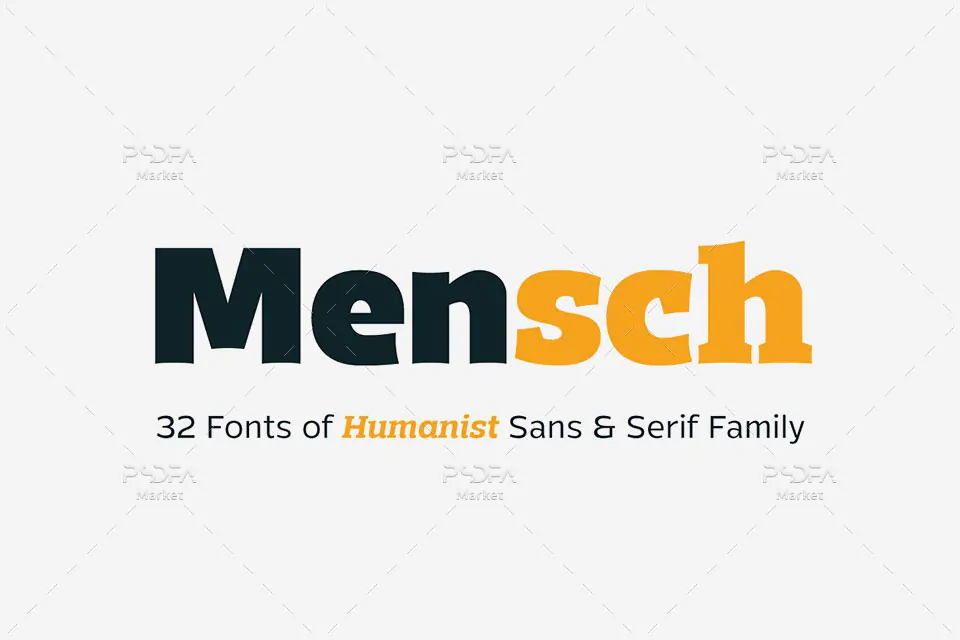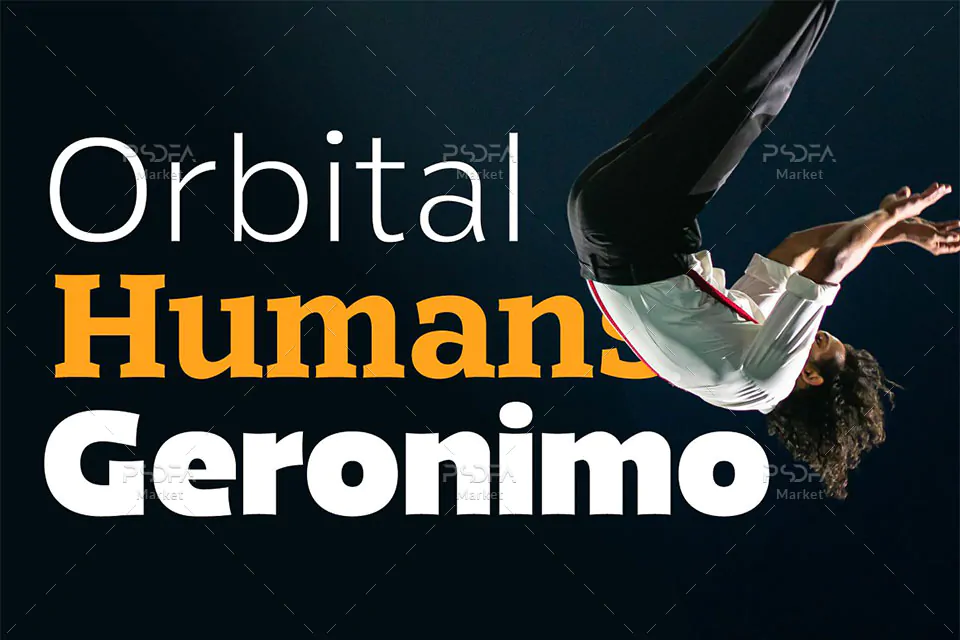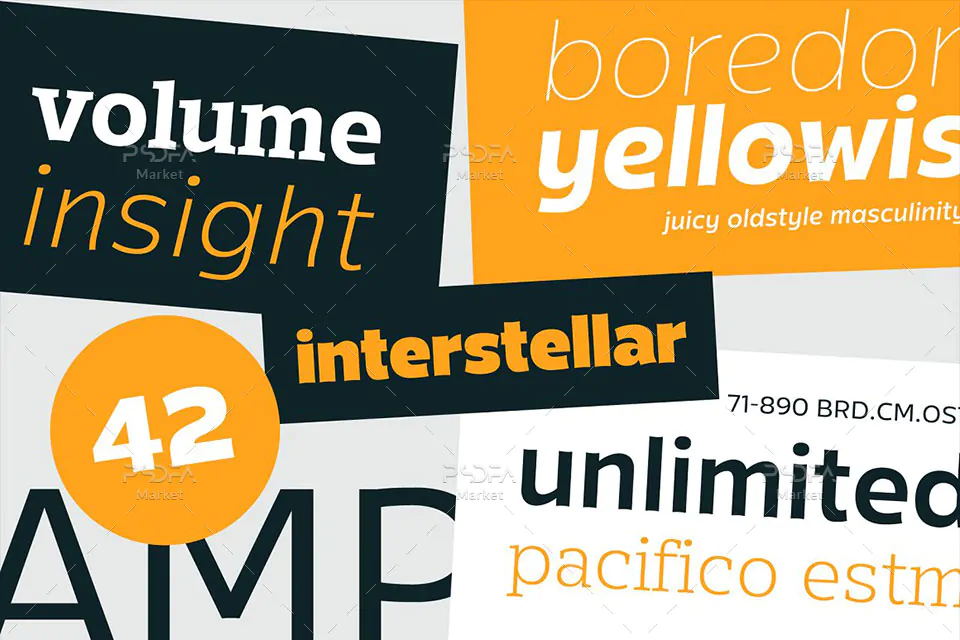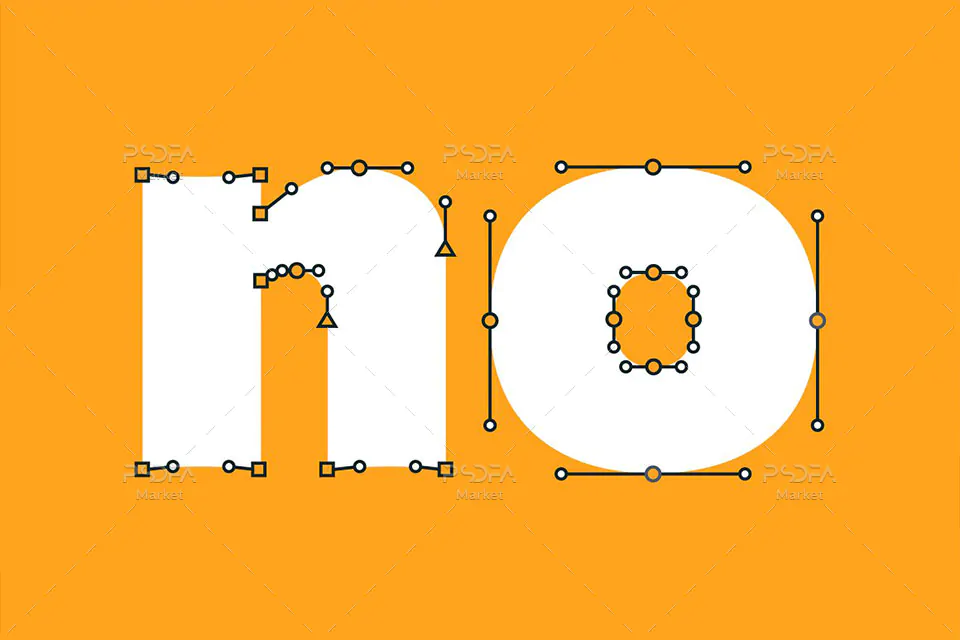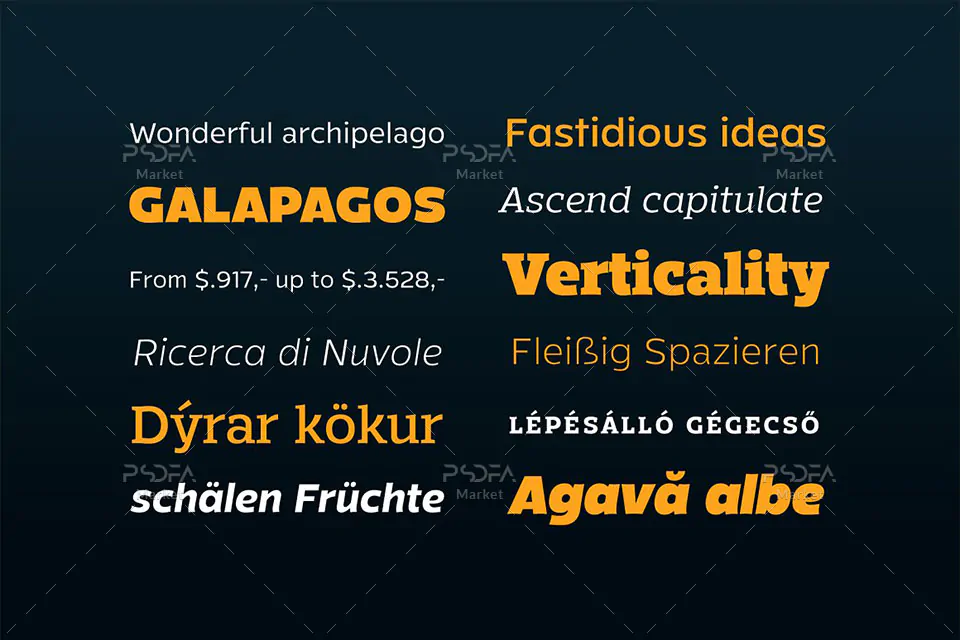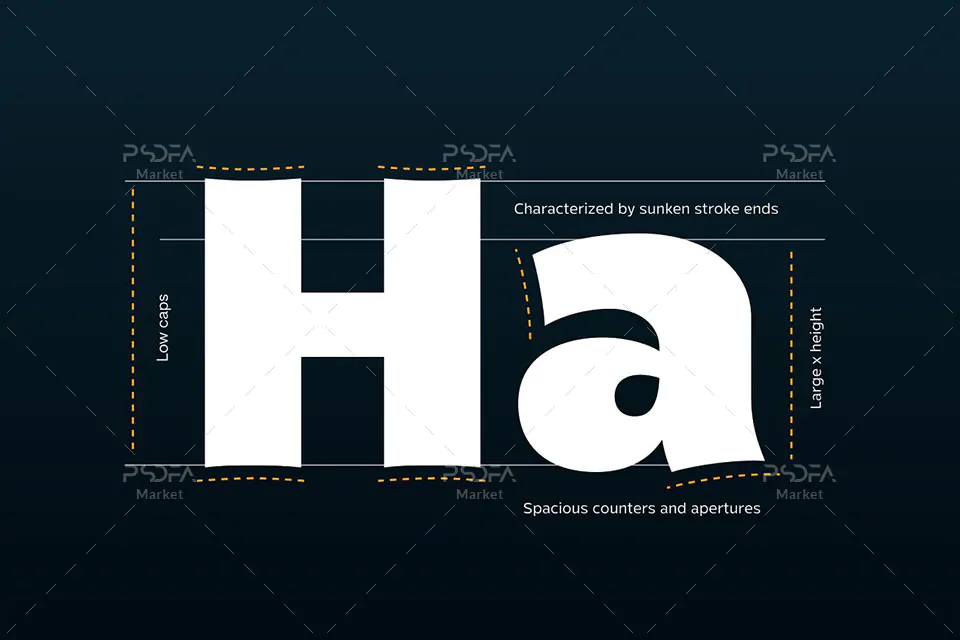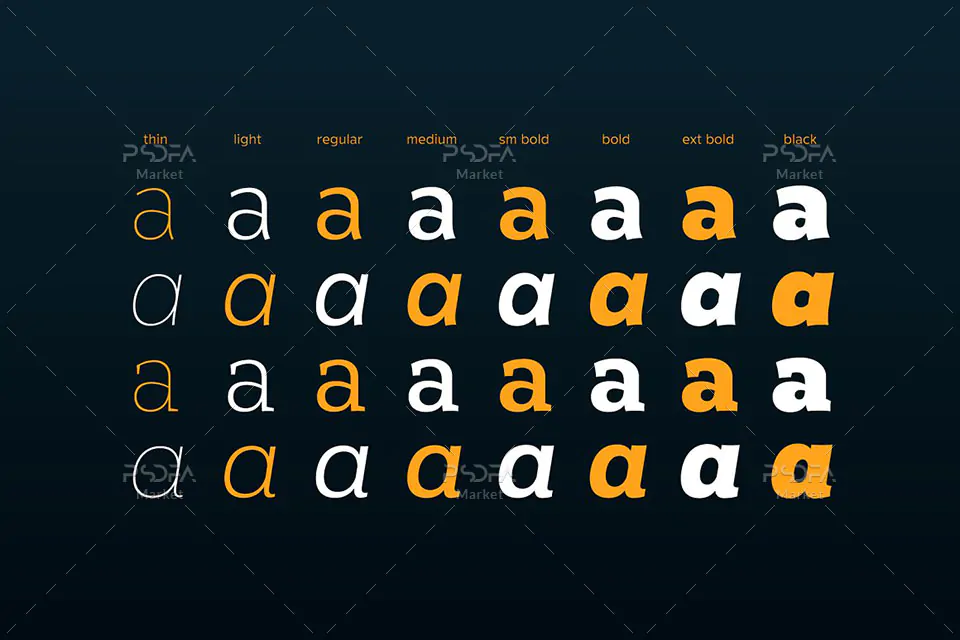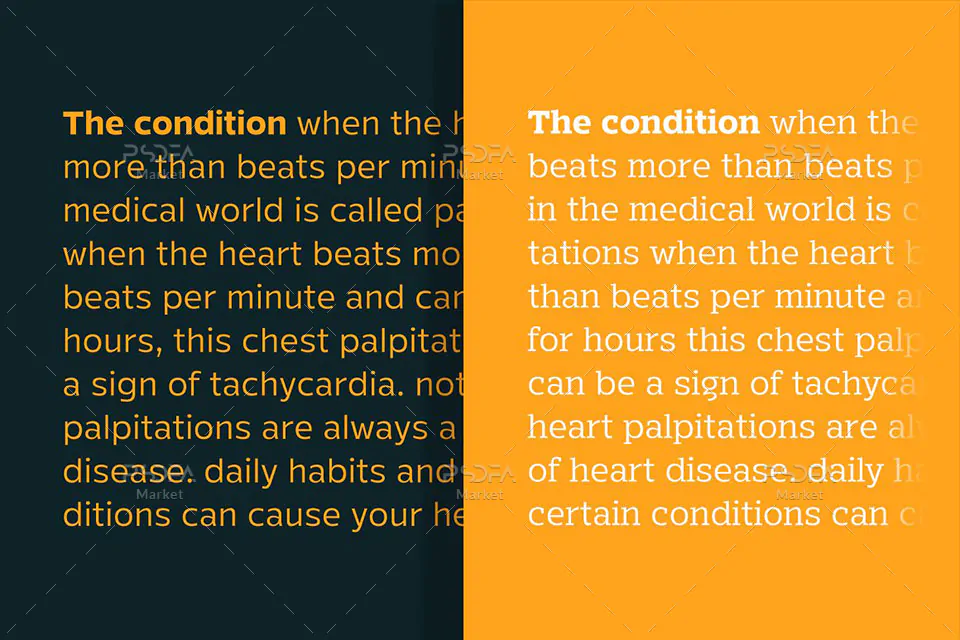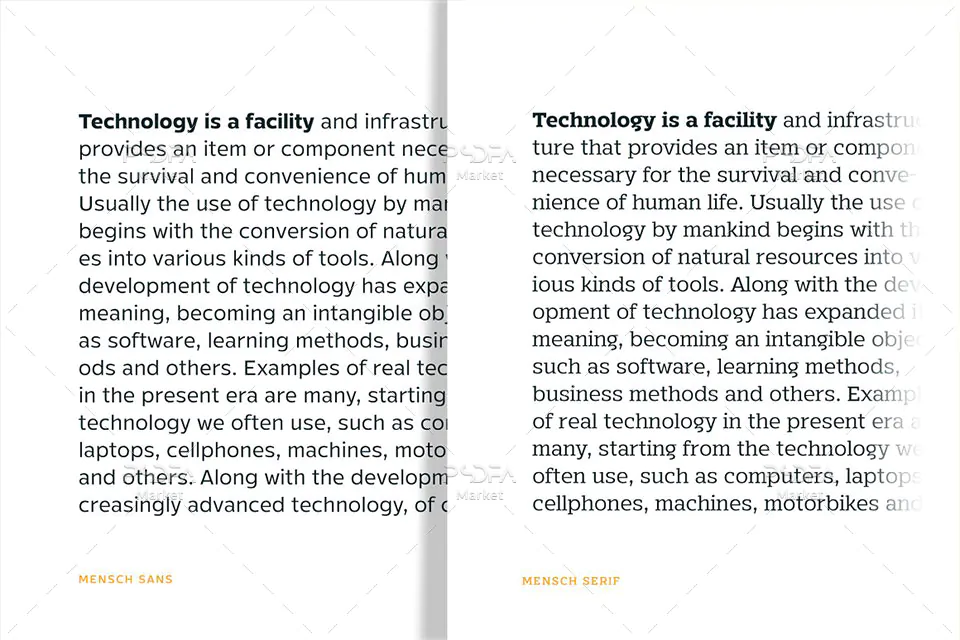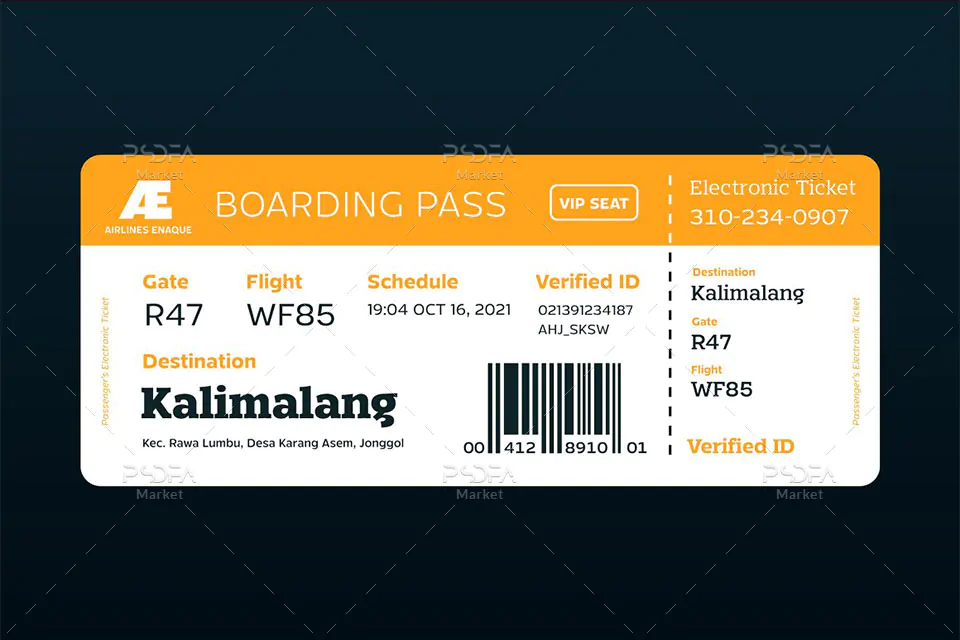
فونت سنس سریف انگلیسی Mensch
فونت سنس سریف انگلیسی Mensch یک قلم زیبای اومانیست از خانواده سنس و سریف است که در 8 وزن مختلف و 440 گلیف متنوع طراحی شده است و مناسب جهت استفاده در طرح و پروژههای گرافیکی مختلف و همچنین طراحی صفحات وب میباشد. این فونت زیبا در قالب 32 فایل OTF در فایل محصول قرار دارد که با نصب آنها در پوشه فونتهای سیستم میتوانید از این فونت انگلیسی در تمام نرم افزارهای گرافیکی و تایپ متون همچون فتوشاپ، افتر افکت، پریمیر، ورد، پاورپوینت و … استفاده کنید.
همانطور که ذکر شد این فونت در 8 وزن مختلف از خیلی باریک تا خیلی ضخیم طراحی شده است و مناسب جهت استفاده در طرحهای مختلف همچون طراحی کارت ویزیت، بروشور، تراکت، انواع بنر و پوستر، تقویم، طراحی صفحات وب و دیگر طرحهای گرافیکی میباشد.
- وزن: 8 وزن مختلف (از خیلی باریک تا خیلی ضخیم) در دو حالت مورب و بولد